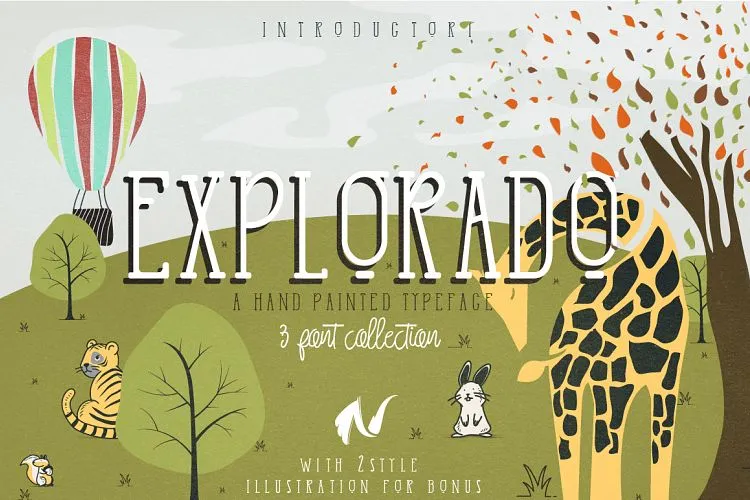
A Explorado Font Family é uma seleção de três belas tipografias que traz características modernas e equilibradas. Esta família inclui serif, sans-serif e estilo tipo na mesma coleção, criando um mix versátil perfeito para diversos tipos de usos. A Explorado Typeface se destaca pela sua textura bem pintada, mantendo a elegância e profissionalismo do tipo serif enquanto se aproxima da leveza e simplicidade das fontes sans-serif. Ela é adequada para uso em logomarcas, embalagens de produtos, convites de casamento, marcas de marca, headlines, sinalização, rótulos, assinaturas, capas de livros, cartazes, citações e muito mais. Com sua versatilidade e qualidade, a Explorado Font Family é perfeita para qualquer projeto onde você precisa de um toque sofisticado que se encaixa na atual tendência moderna. Seja em uma festa de casamento ou uma campanha de publicidade inovadora, a Explorado Font Family está sempre pronta para dar vida ao seu design com suas linhas elegantes e harmoniosas. Obrigatório? Não necessariamente, mas certamente um elemento capaz de destacar seus projetos em uma multidão.